基本書体サブスタイルシリーズ
基本書体サブスタイルシリーズは、様々な場面や媒体の雰囲気に合わせて書体を選択できるように、従来の明朝体・ゴシック体・丸ゴシック体の仮名デザインを変更した派生書体です。
オールドシリーズ
古典的な仮名デザインとなっており、古めかしさを感じさせるような演出ができます。
モトヤ明朝オールド2
モトヤ明朝オールド3
モダンシリーズ
現代的でふところが広い仮名デザインとなっており、文章を組んだ際に安定感を付与できます。
モトヤ明朝モダン2
モトヤ明朝モダン4
モトヤ明朝モダン6
みやびシリーズ
流麗なイメージの仮名デザインとなっており、文章を組んだ際に柔らかい表情を付与できます。また、明朝体・ゴシック体・丸ゴシック体の3ファミリーで、使用場面の雰囲気に応じて使いわけることができます。
モトヤ明朝みやび2
モトヤ明朝みやび4
モトヤ明朝みやび6
モトヤゴシックみやび6
モトヤマルベリみやび5
アンチック体
ゴシック体の漢字と明朝体の仮名を組み合わせた書体となっており、漫画でのキャラクターのセリフ・ふきだし箇所でも、その漫画の世界観や場面の雰囲気を壊すことなく自然なイメージで使用できます。
モトヤアンチック3
使用サンプル
組見本
アンチック体見本
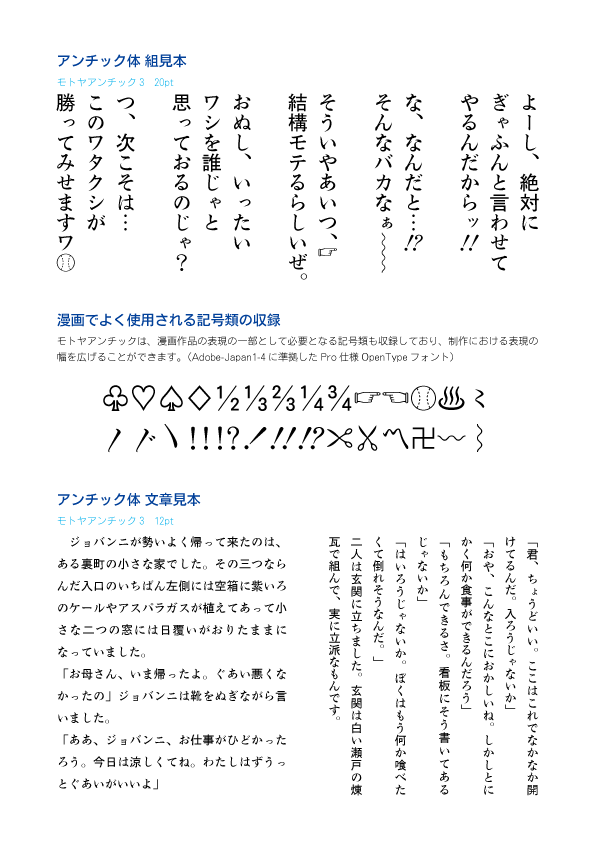
モトヤ明朝オールド比較見本